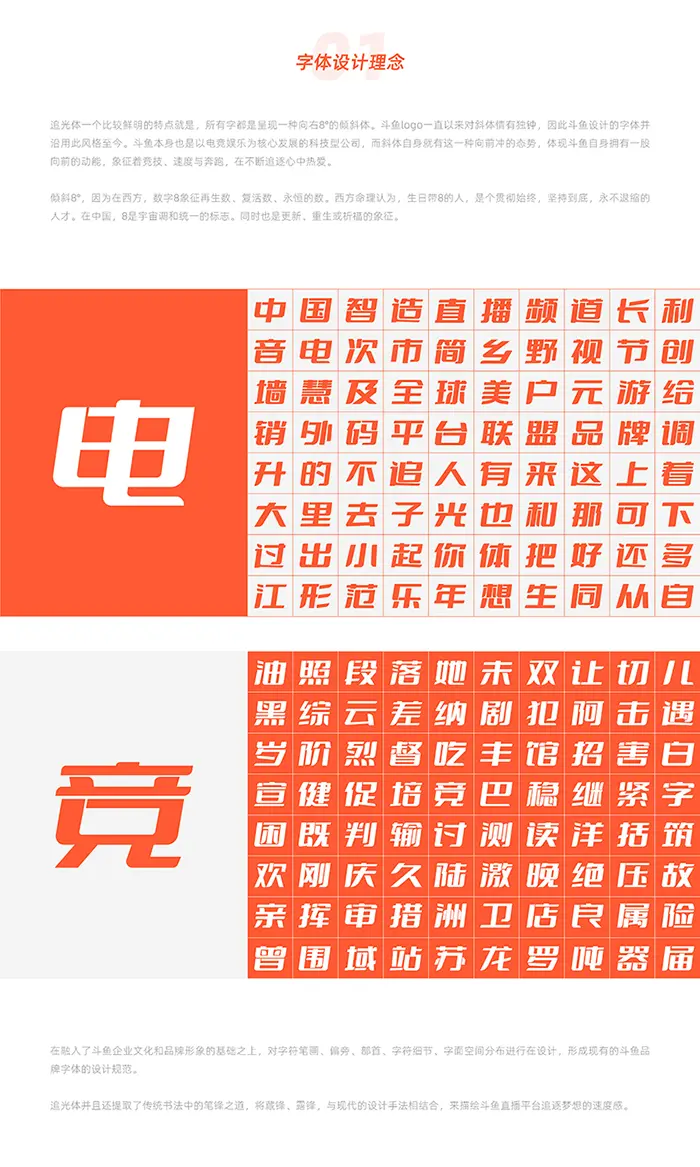
鬥魚追光體,是由鬥魚武漢研發部UED提供指導,品牌組設計成員主導設計的全新品牌字體。很多人會問,鬥魚為甚麼要設計自己的字庫,我們並非心血來潮,作為一個在國內知名的直播平臺公司,我們需要統一的字體來發聲,來表現企業自身的風格,並且向外界傳遞我們自己的品牌特質。我們也想統一公司內所有的子品牌標誌與各項目的宣傳形象,在視覺上用同一種聲音來凸顯鬥魚。我們希望用戶想到鬥魚公司時,是會聯想到一個具有活力、上進,且具有娛樂性質的科技型公司。我們設計團隊也是秉承著這些,來設計這套字體。
鬥魚追光體是符合GB2312簡體中文編碼字符標準的專屬品牌字體。是擁有一種標準版字重,包含6763箇中文字符,100個西文及數字符號。隨著鬥魚品牌場景的日益豐富,鬥魚追光體能逐漸適配平臺的各種場景。